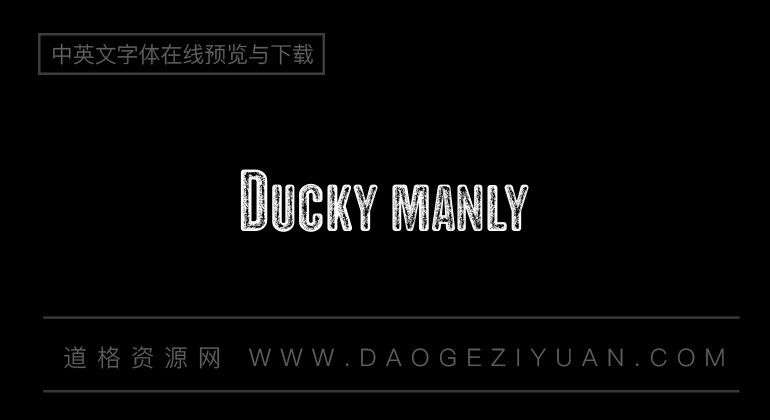
Ducky Manly 字体是一种免费的英文字体,它的设计风格时尚、简洁,给人一种干练、阳刚的感觉。该字体由设计师Hendra Pratama于2018年创作,包含了常见的拉丁字母和数字,可以在Windows和Mac系统上使用。 Ducky Manly 字体的特点是字形饱满、线条流畅,有一定的视觉冲击力。其字体形态笔直刚硬,符合男性审美,适用于各种设计场景,如海报、标志、包装、名片等。 总之,Ducky Manly 字体是一种很棒的英文字体,具有时尚、简洁、阳刚等特点,可以为你的设计作品增添一份优雅和魅力。内容介绍
Ducky manly是一款非常不错的手写艺术字体,具有很好的视觉感,适合于文化类的宣传设计、商业类品牌的广告和产品包装设计以及个性化文字排版等较多场景。